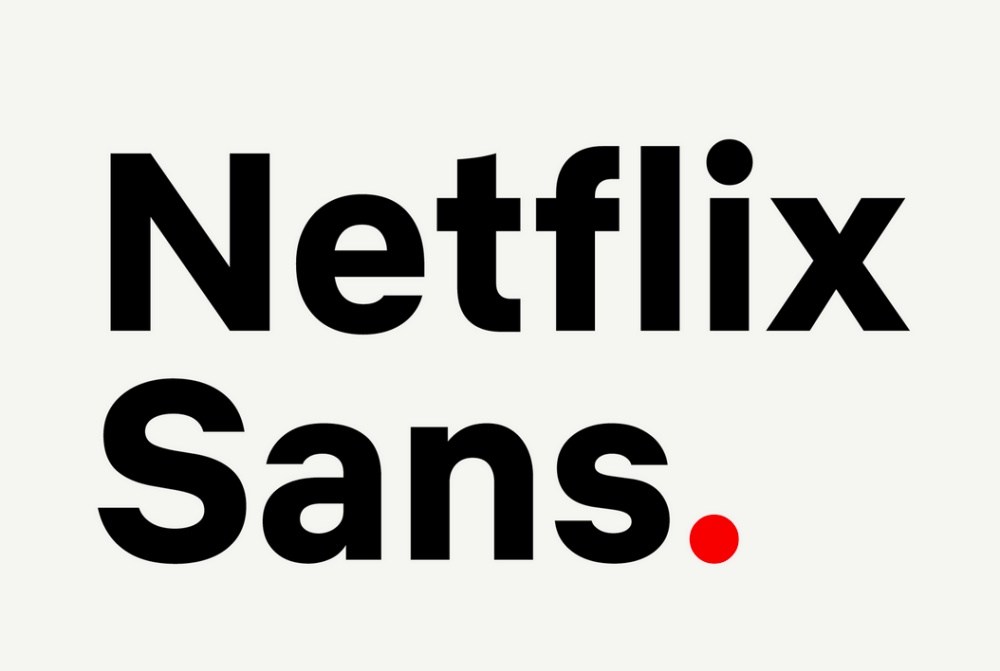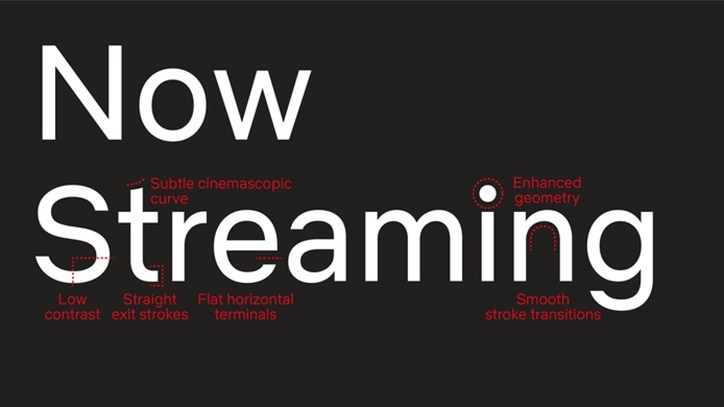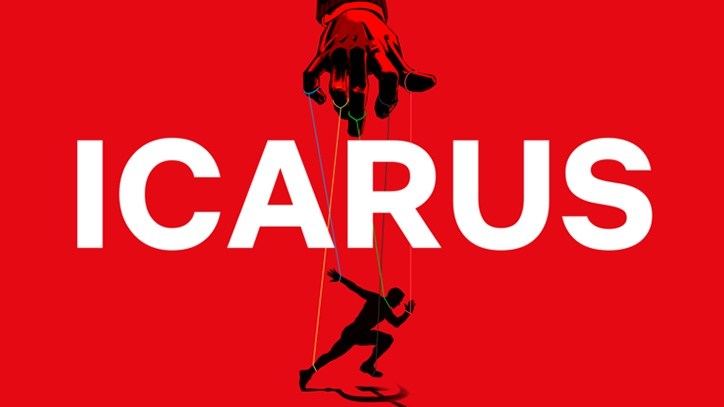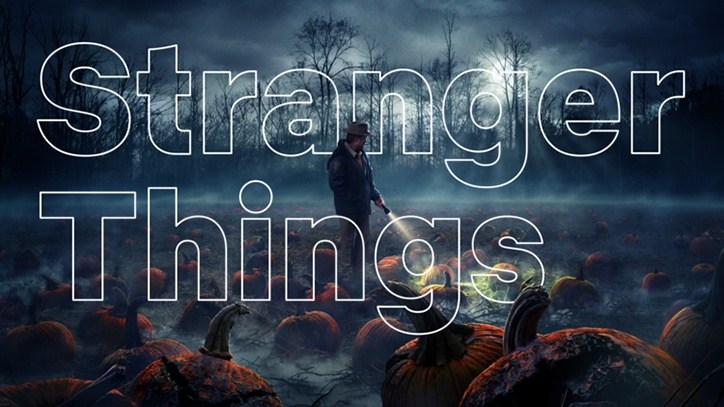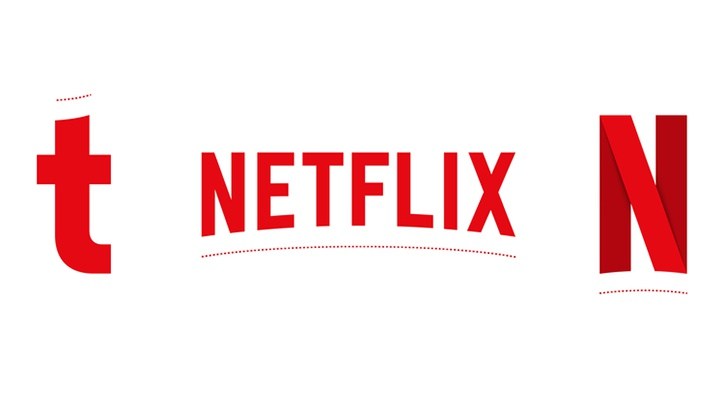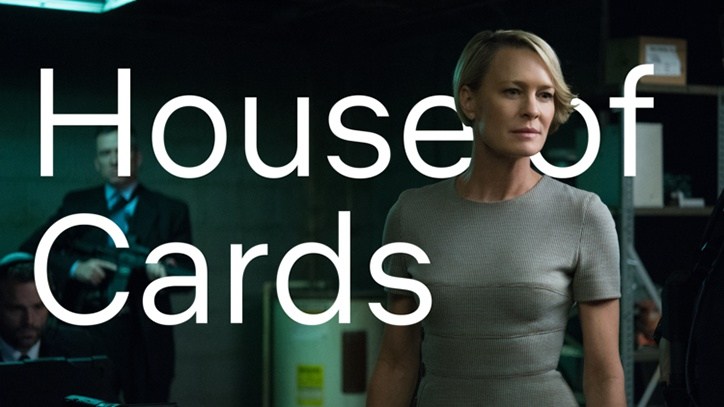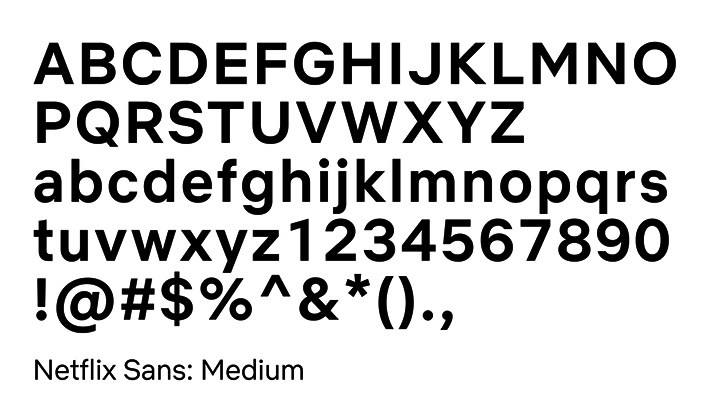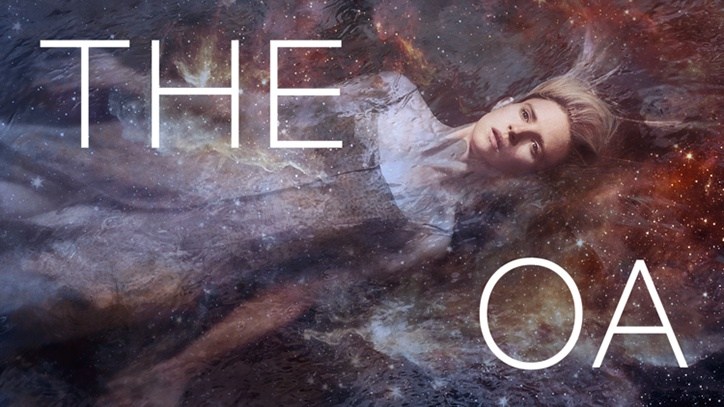
Netflix 藉由更換專屬自有字型 每年節省數百萬美元
在推行許多原創影音內容後,Netflix 稍早宣布將藉由全新創內容-名為「Netflix Sans」的自有字型,減少每年約花費數百萬美元的授權成本支出。
在推行許多原創影音內容後,Netflix 稍早宣布將藉由全新創內容-名為「Netflix Sans」的自有字型,減少每年約花費數百萬美元的成本支出。
根據 Netflix 品牌設計主管 Noah Nathan 表示,過去持續採用的 Gotham 字型,讓 Netflix 每年至少支出高達數百萬美元的字型授權使用費,因此稍早與字型工作坊 Dalton Maag 攜手合作,共同打造真正屬於 Netflix,並且能呈現 Netflix 品牌風格的專屬字型「Netflix Sans」。
「Netflix Sans」基本上可藉由簡潔、清晰字體應用在各類裝置、不同螢幕尺寸規格上顯示,同時在小寫「t」字上方的弧度曲線設計,恰好與 Netflix 制式圖像商標鎖採用曲線弧度相同。
目前使用者應該可以在新版 Netflix 網頁服務內容,或是更新後的 Netflix App 內看見此項字型。而除了實體無框字體之外,Netflix 與 Dalton Maag 還額外打造中空框體字體,以及不同粗細的字體呈現形式,藉此套用在不同宣傳內容。